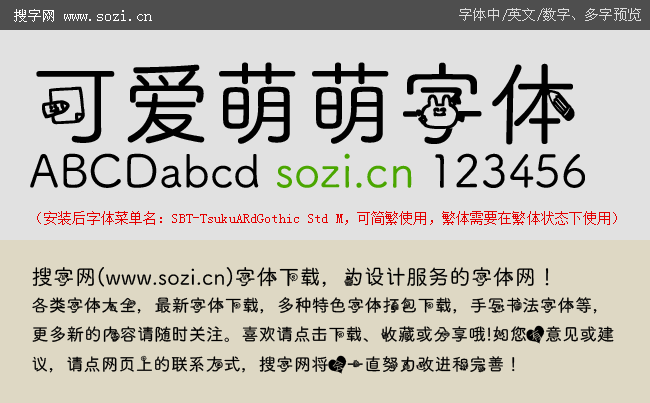
可愛萌萌字體
搜字網(wǎng)給大家提供一款很可愛的手機(jī)中文字體下載。修改者給他起名為可愛萌萌字體,這款手機(jī)字體是在圓體字體筆畫間插入了一些可愛的卡通圖案。趣味性實(shí)足,又保持了文字的識(shí)別度,特別適合喜歡手機(jī)字體個(gè)性一些的朋友在手機(jī)上安裝使用。